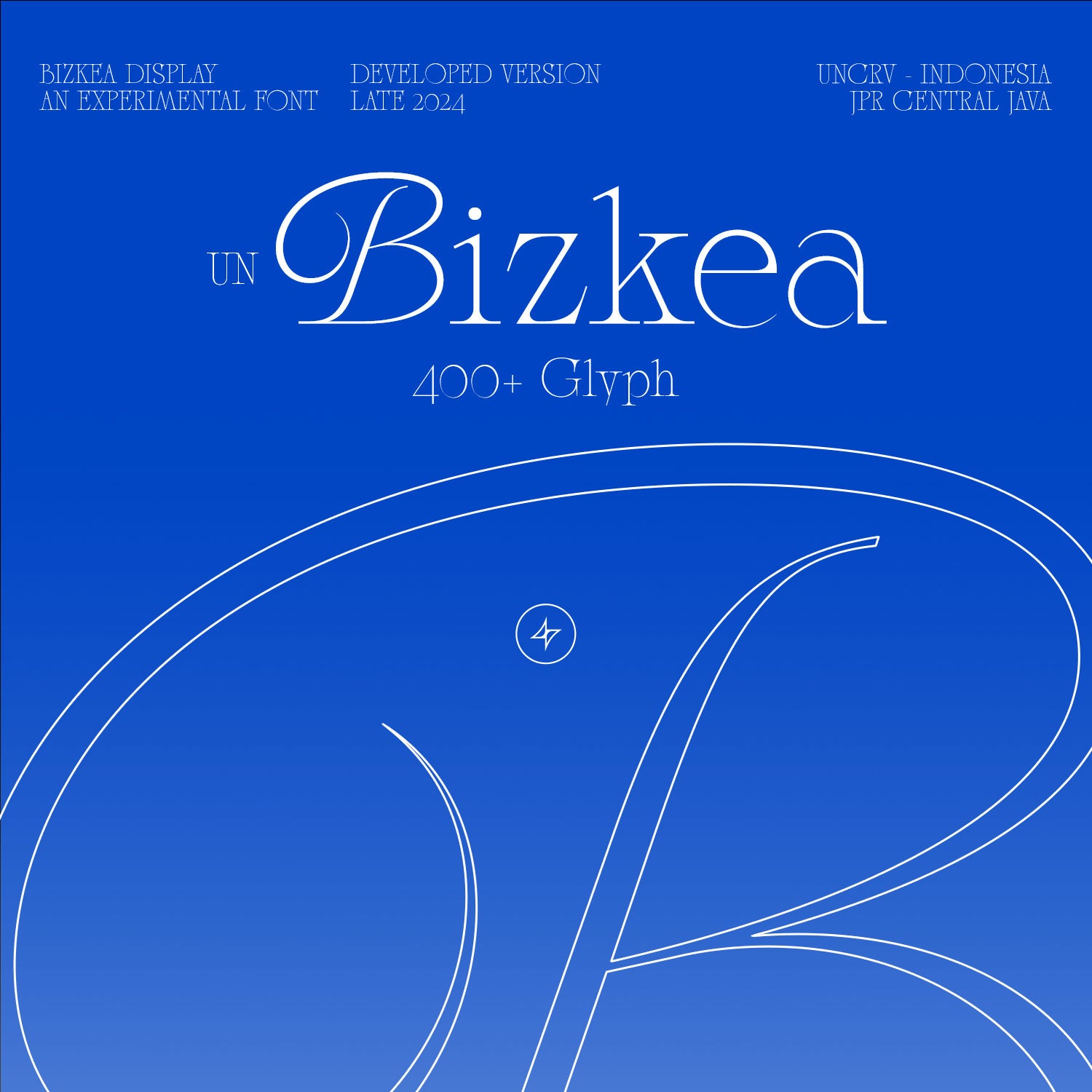
Tipografía Bizkea
Bizkea es una tipografía de exhibición única que combina a la perfección la elegancia clásica de las fuentes Garalde. Al reinterpretar la riqueza artística y visual de estos estilos con un enfoque más moderno y contemporáneo, el resultado es una tipografía atemporal con carácter y versatilidad. Bizkea destaca especialmente en tamaños grandes, logrando un impacto audaz en encabezados y títulos, pero sigue siendo lo suficientemente versátil para diversos contextos de diseño.
Características
• Más de 400 glifos
• Conjunto de caracteres: latino europeo
• Diacríticos
• Ligaduras
• Estilística (1 conjunto)
• Números (3 conjuntos)
• Puntuación
• Símbolos
• Moneda
• Matemáticas